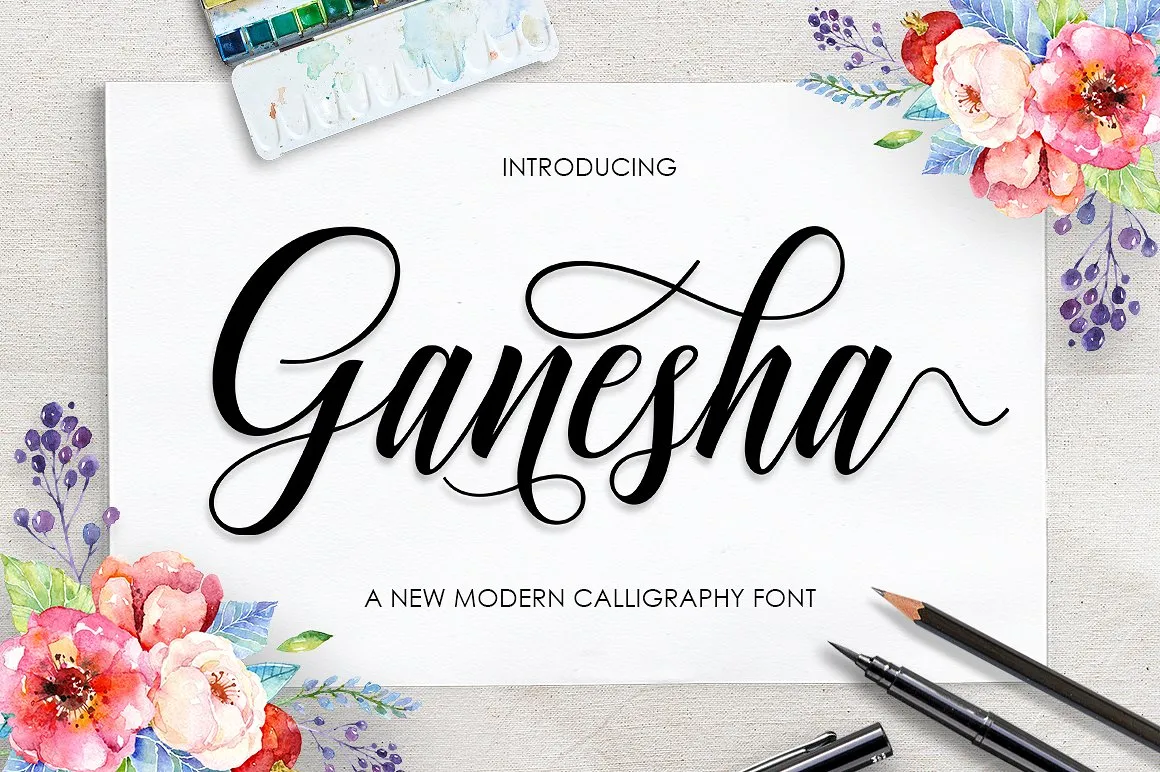
Ganesha Script Font – Download Grátis
A fonte “Ganesha Script Font” é uma novidade na categoria das fuentes de letra script que incorpora elementos do moderno calligrafia contemporânea. Introduzida pelo designer Lettersams, essa fonte traz um ar casual e delicado com suas ornatações sutis. Ganesha não apenas se destaca por sua elegância moderna mas também é versátil, adequada a uma ampla gama de aplicativos, desde logotipos até cartazes e livros, passando por etiquetas, selos e postais de casamento. Suas propriedades fáceis de usar facilitam o uso desta fonte em diferentes contextos e projetos, tornando-a uma excelente opção para designers buscando um estilo que se adapta perfeitamente ao seu trabalho. Engajante e versátil, a “Ganesha Script Font” é uma escolha ideal para qualquer designer profissional que procura uma fonte de letras script moderna e única.